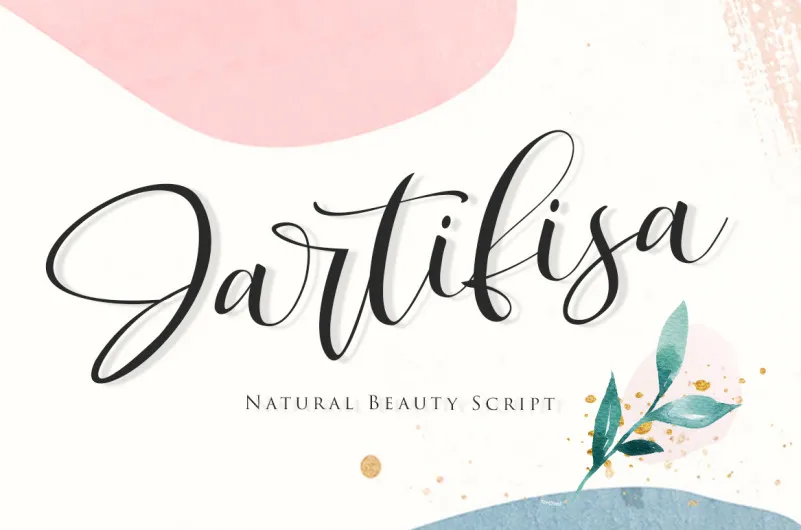
Jartifisa Script Font – Fonte Grátis
Jartifisa Script Font
A Jartifisa Script Font é uma tipografia com traços sólidos e divertida inspirada no encanto natural das flores. Seus traços fluidos e orgânicos parecem crescidos na suavidade dos petalões, fazendo você mergulhar em seu encanto único. Esta fonte é perfeita para adicionar uma pitada de vida à qualquer arte floral ou decoração da primavera. Transforme suas criações com uma graça que surpreende e eleva seu trabalho a um novo nível. É como pegar uma obra-prima florido e dar-lhe uma forma visual que vai fazer seus projetos brilhar ainda mais. Seja você um decorador de jardins, criador de papelaria ou até mesmo um artista de arte digital, a Jartifisa Script Font é ideal para transformar suas ideias em obras de arte única e encantadora.